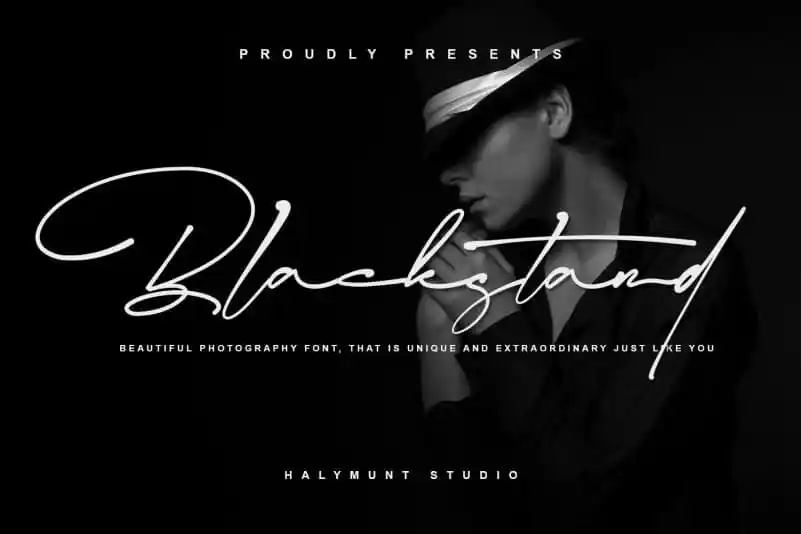
A Blackstand Script Font é uma escolha inteligente para quem busca adicionar um toque natural e autêntico a seus projetos de design. Inspirada na escrita real, esta fonte cíliar oferece o estilo e a aparência do trabalho cuidadosamente elaborado à mão. É perfeita para diversas aplicações, desde marcas e logomarcas até embalagens de produtos, impressões digitais e invitações, destacando-se por seu estilo único que transmite confiabilidade e qualidade. Seja qual for o projeto em que você está trabalhando, a Blackstand Script Font certamente adicionará um toque especial de originalidade à sua proposta visual. Esta fonte cíliar é uma ótima opção para projetos que buscam transmitir uma sensação autêntica e cuidadosa, tornando-a a escolha perfeita para qualquer projeto gráfico em que você deseje incorporar um toque de personalização natural.